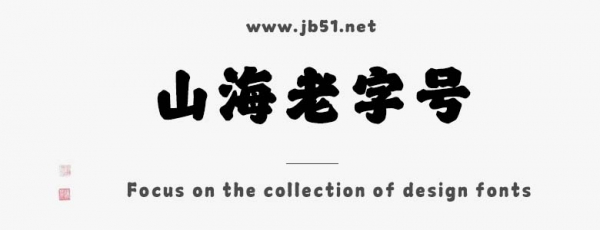
山海老字號(hào)W是由山海字庫(kù)出品的字體,這款字體筆觸粗實(shí),字形端正,具有很好的視覺(jué)感,適合應(yīng)用于藝術(shù)設(shè)計(jì)、平面宣傳設(shè)計(jì)、網(wǎng)頁(yè)設(shè)計(jì),書法字帖等領(lǐng)域,需要的朋友可以前來(lái)本站下載。